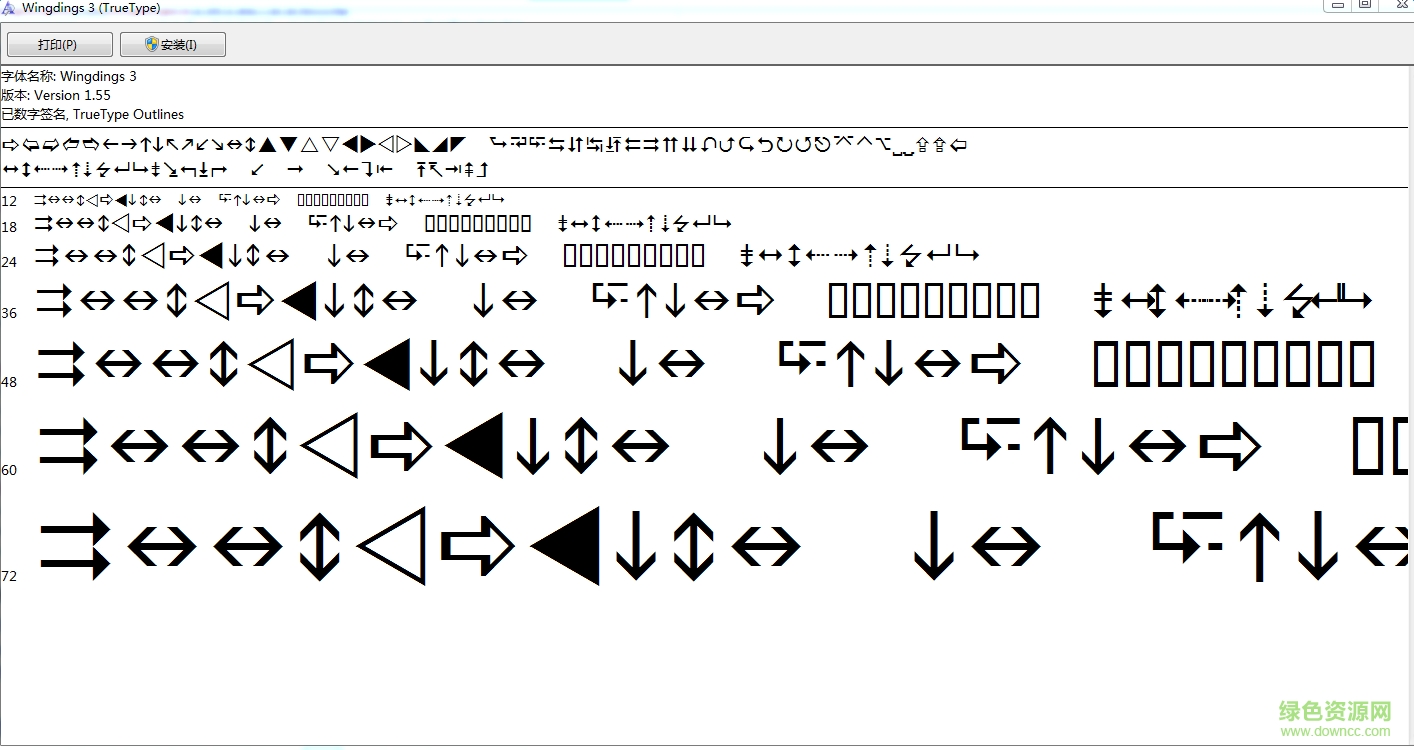
wingdings3.ttf字體是一款獨(dú)特的符號(hào)字體,該字體將所有的英文字符全部轉(zhuǎn)換成特殊符號(hào),在需要輸入一些箭頭符號(hào)的時(shí)候可以使用這款字體,有需要的朋友歡迎在綠色資源網(wǎng)下載!
Wingdings 3字體介紹
Wingdings 3 是微軟office和一些微軟相關(guān)產(chǎn)品內(nèi)預(yù)置的TrueTypedingbatfont符號(hào)字體。該字體由Type Solutions, Inc.公司在1990年開發(fā)。Wingdings3 包含了箭頭形狀的全部種類。